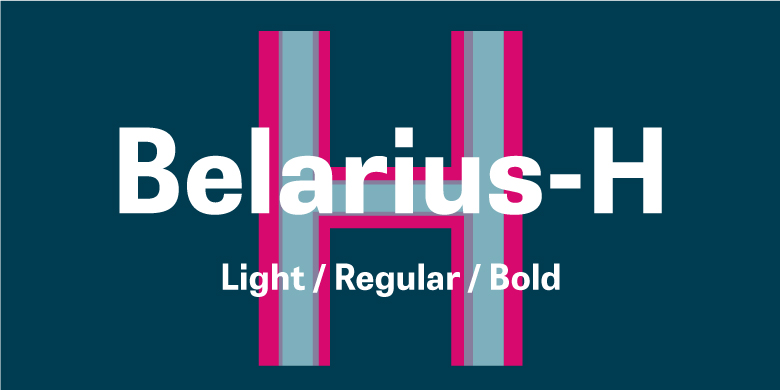
Belarius-H
Belarius-H,这款字体结构工整、笔画清晰,兼顾美观与易读性,适用于标题、正文、海报、包装、LOGO 等多种场景。字形优雅稳定,风格百搭耐看,适配日常排版与创意设计,让文字呈现更舒适、更具质感。Belarius-H一笔一画,皆是细节,以均衡的比例、流畅的线条打造舒适视觉体验,字形端正大气,风格简约现代。无论是商业设计、品牌宣传还是日常排版,都能轻松驾驭,让文字更有格调与力量。Belarius-H字体下载。
字体品牌: TypeTogether 设计师:荷西·斯卡格里欧纳(José Scaglione) 字体分类:无衬线体 字体属性:外文 字符集:Unicode 发布时间: 2024